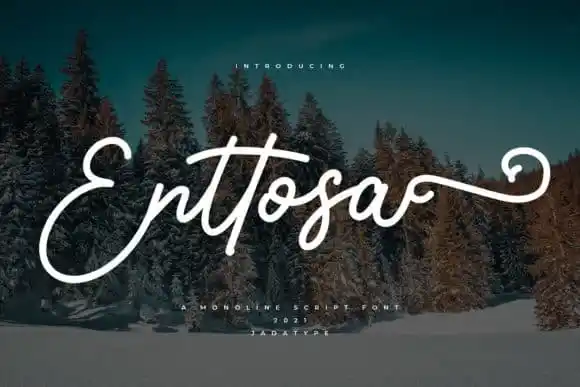
Enttosa Script Font – Download Grátis
A Enttosa Script é uma fonte script que apresenta elegância e simplicidade, projetada por jadatype para os profissionais de design gráfico. Perfeita para complementar nomes de marcas, logotipos e identidades visuais, sua versão multilíngue oferece suporte a múltiplas línguas, algo que valoriza especialmente na era digital em que vivemos. Com ligaturas e caracteres especiais refinados, ela é ideal para se integrar às necessidades de branding moderno e sofisticado. Instalada facilmente nas aplicações gráficas populares como o Adobe Family, Affinity e outras ferramentas, Enttosa Script torna-se uma escolha segura para qualquer projeto que exija uma fonte elegante e versátil. Com ela, você pode criar designs únicos em diversos formatos de mídia social, anúncios e identidades digitais sem comprometer a qualidade da sua criação.